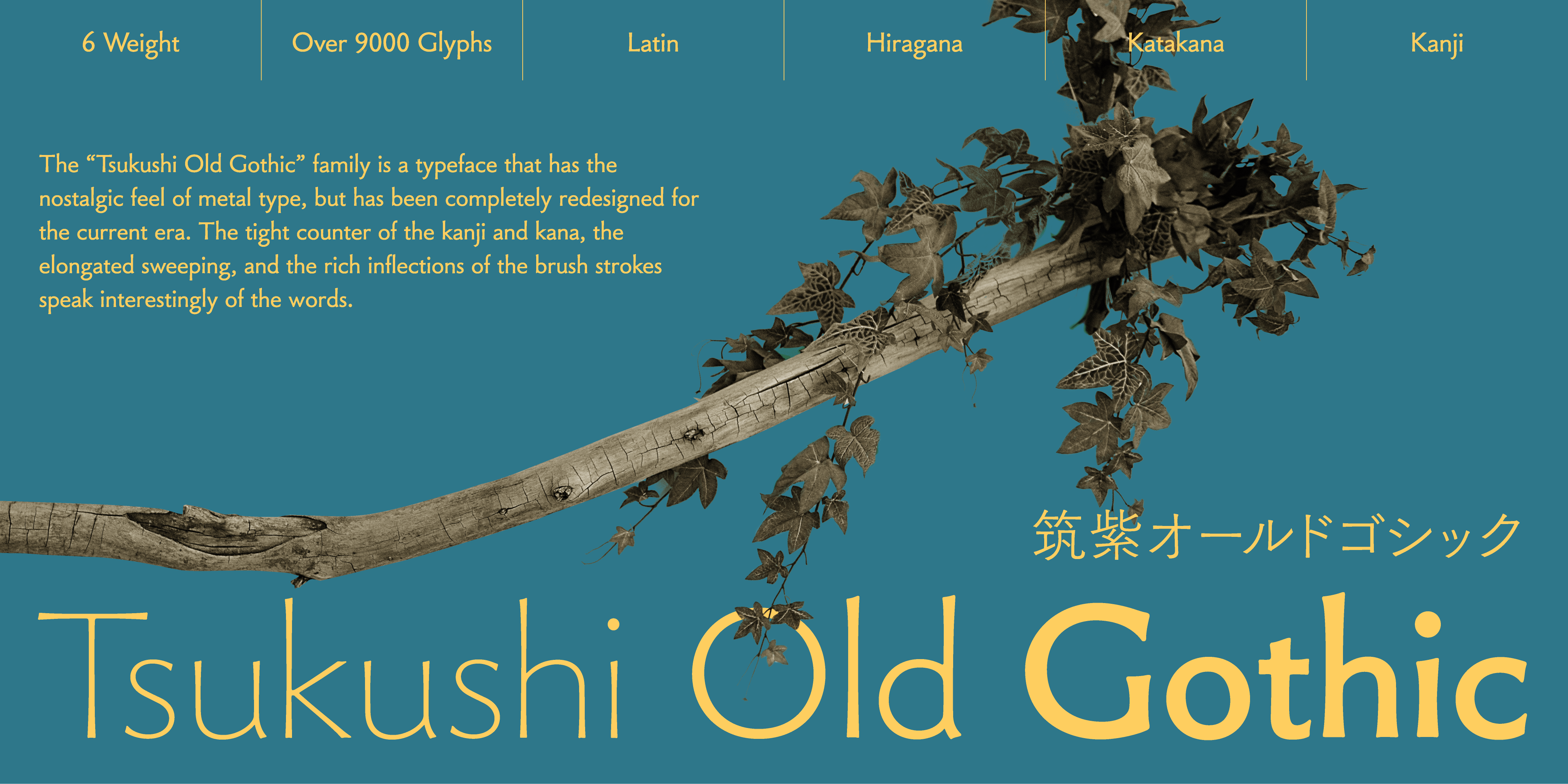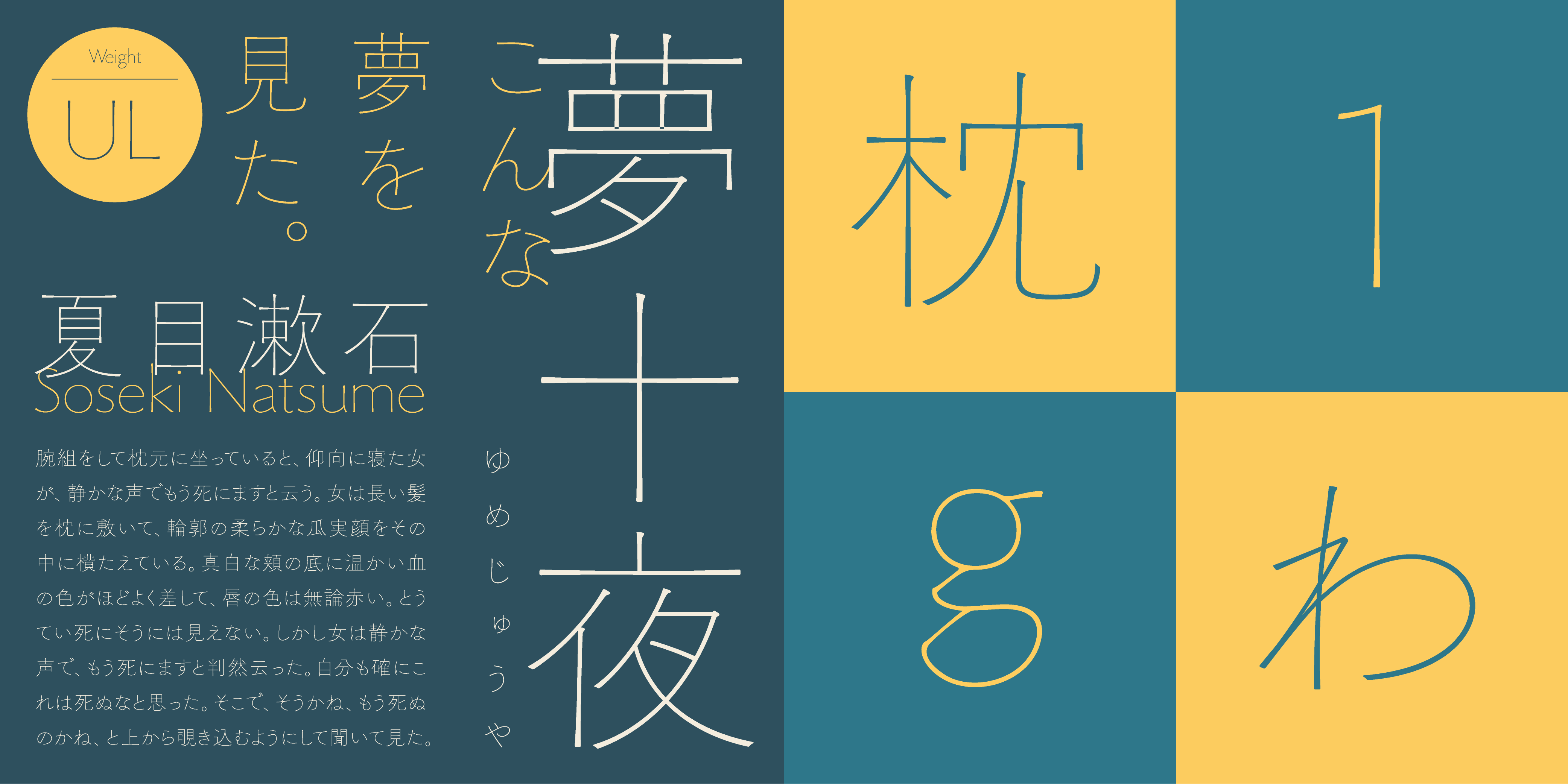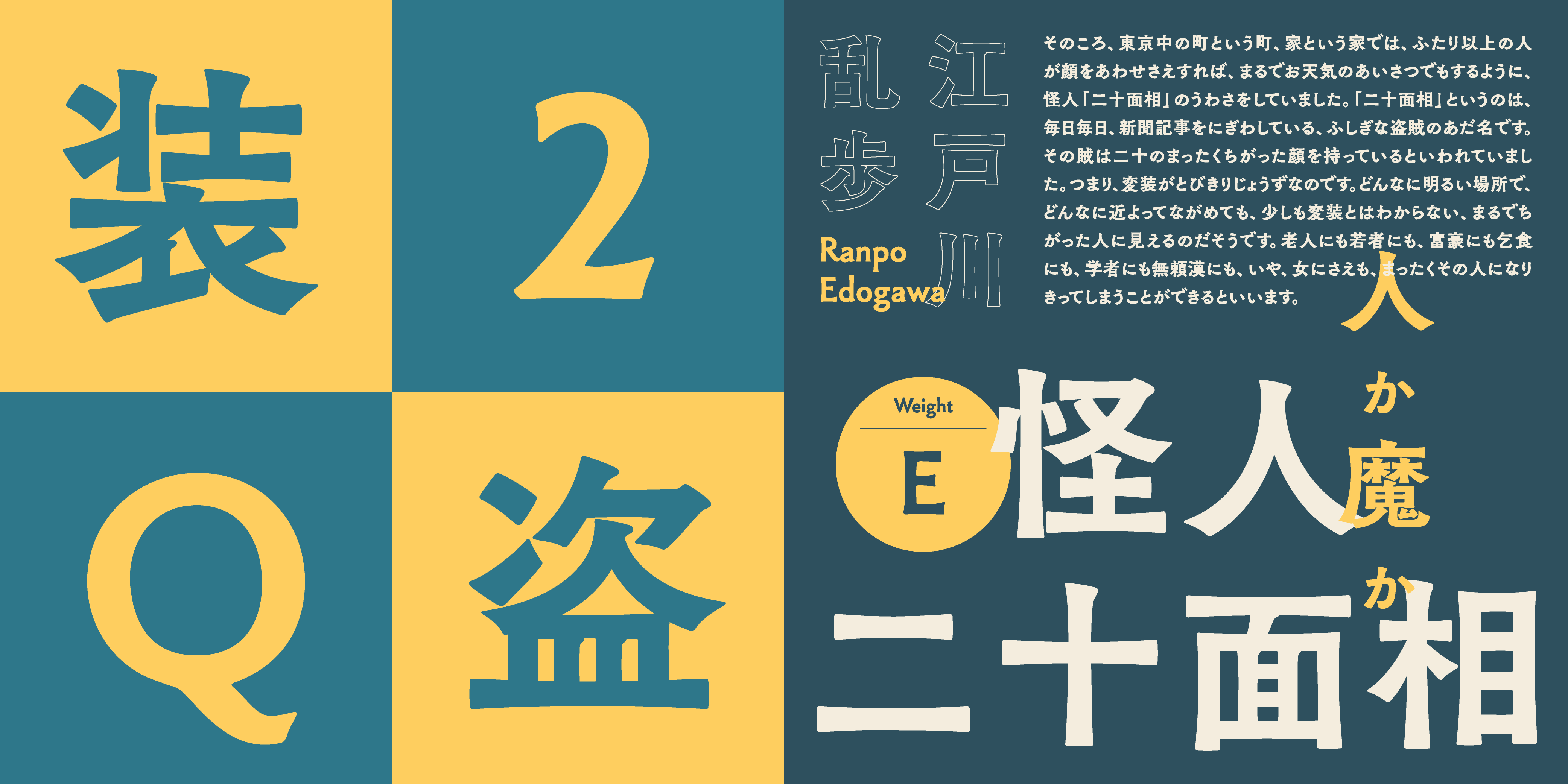
Tsukushi Old Gothic 是一款融合传统与现代美感的日文字体,其独特之处在于:摒弃了机械式的直线与锐角,转而采用温润柔和的曲线设计,让字形充满人情味与手写质感。相比常规哥特体,它保留了适度的笔触流动感,呈现出清新自然的节奏与氛围。
粗字重版本如 Tsukushi Old Gothic B,线条收放之间展现「喇叭状」造型,营造出稳重大气的视觉印象。撇捺笔势则动感十足,笔画末端舒展有力,带来凛然的书写风貌。
极细版本 Tsukushi Old Gothic UL 更是实现前所未有的纤细与精度,让字体在大字号下也能展现出有机而流畅的细节。
整体而言,这是一款兼具古典气质与现代工艺的哥特体,尤其适合追求温度与品位的排版设计。